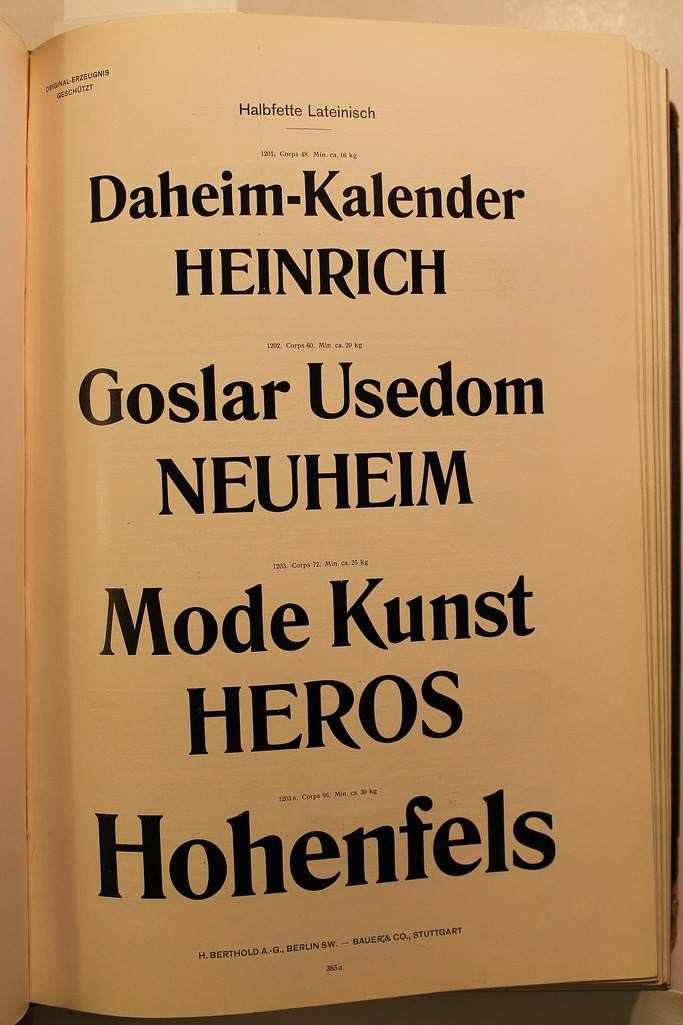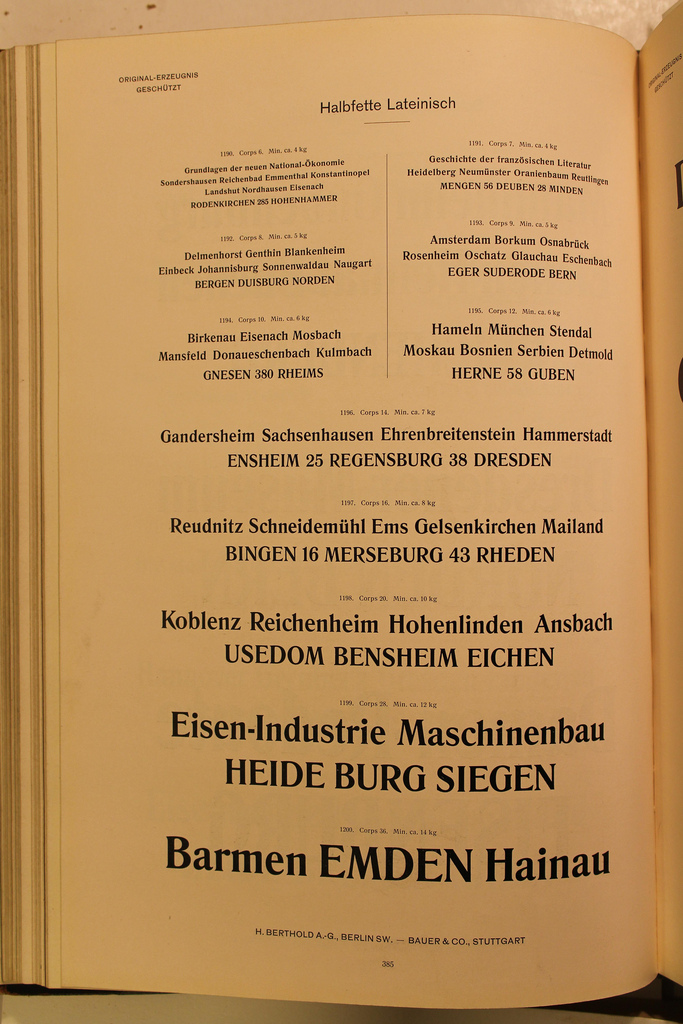
Minister-ähnliche Serif, Radio Wien 1924-38
Hm, auf jeden Fall ähnlicher als alles, was ich bisher gesehen habe.
Allerdings ganz anderes 'J' (geht uA nicht unter die Grundlinie (in meinem Beispiel leider nicht zu sehen)), weniger starke Slab-Tendenz und ganz andere Ziffern.
Es ist wahrscheinlich eine dieser beiden Schriften, die fast identisch sind:
Römisch von D. Stempel AG, Franfurt a. M. von 1914
oder
Romanisch von C. E. Weber, Stuttgart von 1932.
Ob hf. oder normal lässt sich bei deiner Vorlage wegen des Quetschrands nicht genau erkennen.
Leider habe ich keine gute Vorlage zur Hand